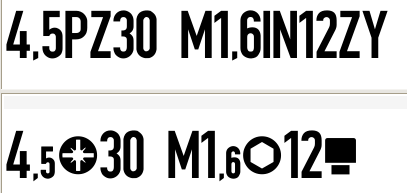
Schraubensortiment etikettieren (bei wenig Platz: 17 mm × 4,6 mm)
Manchmal sind die Fehler nur klein, die Wirkung aber fatal. Ich hatte ja bei den Seitenansichten auch diesen abgerundeten Senkkopf eingeführt und dem die Aufrufcode RS gegeben, für Rundsenk. Dabei hatte ich übersehen, dass ich für den Innenvierkant (Robertson-Antrieb) für Robertson auch RS benutzt hatte, das habe ich jezt in RO geändert.
Hier jetzt noch nal die korrigierten Codes plus der PUA-Codeplätze für Nutzung ohne OpenType:
SL oder Schlitz = die Schlitzschraube für flache Schraubendreher, U+E007
PH oder Kreutzschlitz = den klassischen Philips-Kreuzschlitz, U+E000
PZ oder Spax = Pozidriv, U+E001
TX oder Torx = Torx, U+E001
TS oder Torxsicher = Torx mit Innenstift, U+E00B
ATX oder Außentorx = Außentorx, U+E003
IN oder Inbus = Innensechskant (heißt übrifens nicht Imbus, wie oft gesagt wird), U+E004
IS oder Inbussicher = Innensechskant mit Mittelstift, U+E00C
SP oder Spanner = Spanner, das ist die Sicherungsschraube mit den 2 Löchlein, U+E00A
TW oder Triwing = Triwing, U+E008
TQ oder Torqset = Torqset, U+E009
RS oder Robertson = Innenvierkant, U+E00D
SK oder Sechskant = Sechskant, U+E005
VZ oder Vielzahn = Vielzahn, U+E006
ZY oder Zylinder = Zylinderkopf, U+E010
FL oder Flach = Flachkopf, U+E012
LK oder Linse = Linsenkopf, U+E013
HR oder Halbrund = Halbrundkopf, U+E014
SE oder Senk = Senkkopf, U+E015
RS oder Rundsenk = ausgerundeter Senkkopf (bei Spax üblich), U+E016
Es führt zwangsläufig dazu, dass die Schrift eine geringere Größe haben müsste.
Nicht unbedingt. Hier mal ein Vorschlag, wie ich an Deiner Stelle rangehen würde – Variantenbildung:
1) FF Fago Extended Black, 12 pt
2) Catfonts Schraubenkoeppe + FF Fago Condensed Bold, 12 pt
3) Catfonts Schraubenkoeppe + FF Fago Condensed Bold, 11 pt
4) Catfonts Schraubenkoeppe + FF Fago Condensed Bold, 11 pt
Das könnte man noch weiter treiben, zum Beispiel mit weiteren Schrifttypen und Kombinationsversuchen; dann eventuell noch mal zur Diskussion stellen, wenn Du mit mehreren Rückmeldungen unterschiedlicher Natur leben kannst; testdrucken und ggf. auch mal entsprechend aufkleben um es im Zshg. mit der Verpackung besser bewerten zu können; entscheiden; auf alle Daten anwenden; ausdrucken; fertig.
Man könnte hier sogar noch Platz sparen, wenn man die Schrauben-Icons anstatt des Bullets (•) als Trennzeichen in die Mitte zwischen die Ziffern nimmt. Ein Malzeichen (welcher Form auch immer) ist zwar Usus, aber keinesfalls nötig (und strenggenommen sogar ziemlich unlogisch). Einen funktionalen Mehrwert haben die Icons durchaus.
Kommt aber auch immer etwas darauf an, wo der Fokus liegt: Soll der Betrachter erstmal schnell erkennen, um welche Art oder um welche Größe der Schrauben es sich handelt?
Man könnte sich das Trennzeichen auch schenken, wenn man eine der beiden Größen negativ, sprich weiß auf schwarzem Grund, drückt. wobei dass natürlich davon abhängt, ob der Drucker das kan …
Hieße aber auch Schriftverkleinerung, es sei denn man kann von randabfallendem Druck ausgehen. Ansonsten könnte man auch noch mal mit ausreichendem Leerraum oder Strichstärken-Wechsel experimentieren.
Und falls jemand¹ Lust haben sollte, statt der Vera Sans eine (ebenfalls frei veränderbare) schmale Schrift für Buchstaben und Ziffern zu benutzen, die Brüche und tiefgestellte Ziffern gleich mit bringt, könnte man diesen so modifizierten Schraubenkoeppe-Font evtl. sogar für komplette Labels einsetzen. Eine Kandidatin ist vielleicht die Encode Sans Compressed (vielleicht der SemiBold-Schnitt? :-?).
3%E2%82%85%20%C2%B7%2045%C2%BD.png
Statt · könnten dann die Schraubensymbole stehen; ansonsten vor oder nach den Maßen. (Die Längenangabe ist unsinnig, aber so gewählt, um ½ und ₅ unterbringen zu können.)
1. Das muss ja nicht catfonts sein. Das Tolle an OFL- und ähnlichen Lizenzen ist ja, dass jeder solche ein „Mashup“ aus Encode Sans und Schraubenkoeppe herstellen darf.
Vielen Dank für Deine Skizzen.
Ich werde die Ideen mal sacken lassen und mit schmalen Schriften experimentieren.
Da es sich um ein Sortiment handelt, auf welches man von oben draufschaut (siehe Link im Ausgangsposting) und die Schrauben (und andere Objekte wie Nägel, Dübel und Maschinenschrauben) unmittelbar sehen kann, neige ich dazu, eher wenig als viele Informationen im Etikett unterzubringen.
Etwas länger: Was Support für Opentype-Funktionen angeht, hinken LibreOffe und OpenOffice.org kommerzieller Software zur Zeit tüchtig hinterher. :cry: XeLaTeX kann praktisch alle Opentype-Funktionen, Gimp und Scribus bieten eingeschränkte Unterstützung für Zwangsligaturen.